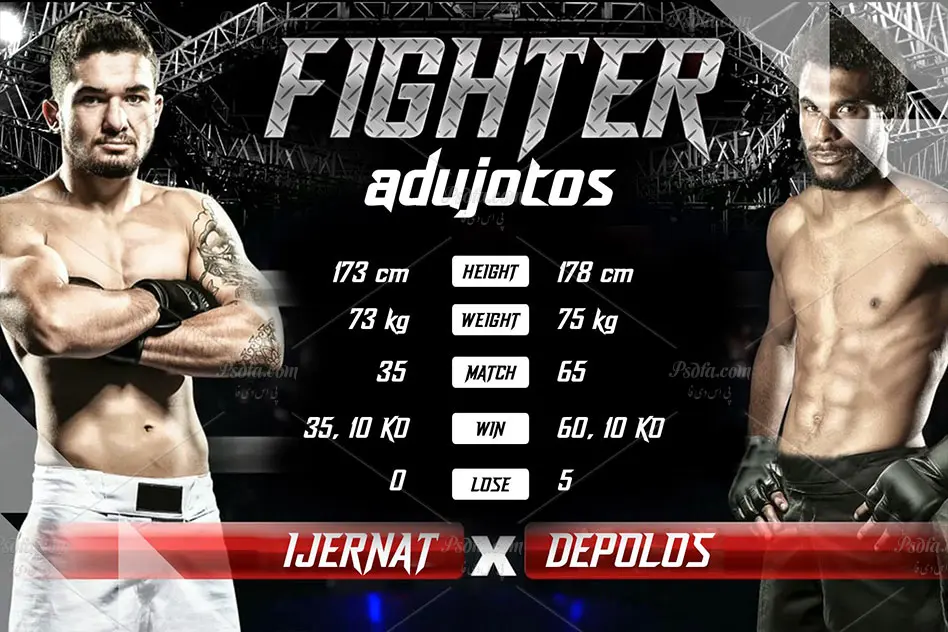
فونت اسپرت و ورزشی Dash Horizon مناسب برای طراحی گیم (Game)
فونت اسپرت و ورزشی Dash Horizon
در این مطلب شاهد فونت اسپرت و ورزشی Dash Horizon مناسب جهت استفاده در طراحی و گرافیک به خصوص طراحی انواع گیم و پوسترهای ورزشی می باشید. این فونت انگلیسی فوق العاده زیبا در قالب 2 فایل otf و ttf بر روی سایت قرار گرفته است که پس از نصب یکی از این دو فرمت در پوشه فونت های سیستم خود قادر به استفاده از آن ها در تمام نرم افزارهای گرافیکی و ویرایشگر متن از جمله نرم افزار فتوشاپ ، پریمیر ، افترافکت ، ورد و … خواهید بود. فونت Dash Horizon در وزن معمولی (Regular) طراحی شده است که آن را می توان در تیتر و عناوین طرح های گرافیکی مورد استفاده قرار داد.
- نام فونت : Dash Horizon
- وزن : معمولی (Regular)